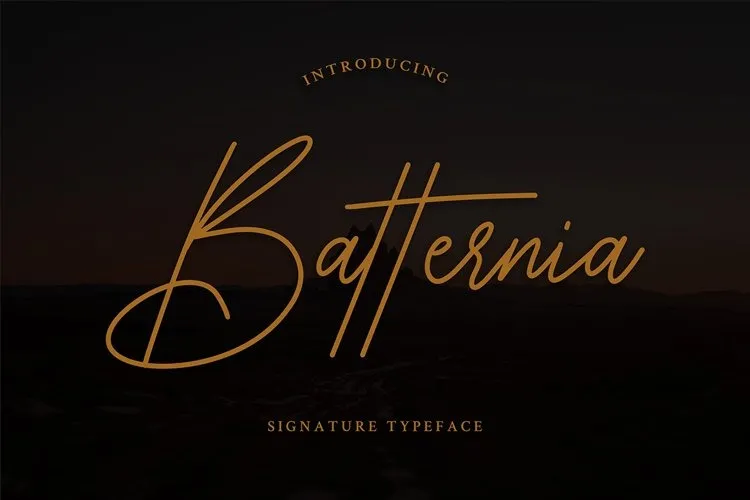
A Batternia Font é uma tipografia script monoline que traz estilo e personalidade, criada pelo designer de fontes Formatika Studio. Seus traços elegantes e engraçados se destacam na categoria de fonts scripts. Ela será um perfeito complemento para projetos de branding, logomarcas, designs de casamentos, postagens em redes sociais, anúncios, embalagens de produtos, design de produto, selos, fotografia, marca d’água, convites e materiais de papelaria. A Batternia está aqui para aqueles que buscam uma fonte divertida e criativa, ideal para agregar um toque único a vários tipos de projetos visuais. Experimente sua autenticidade e charme na próxima vez que estiver trabalhando em um projeto visual.